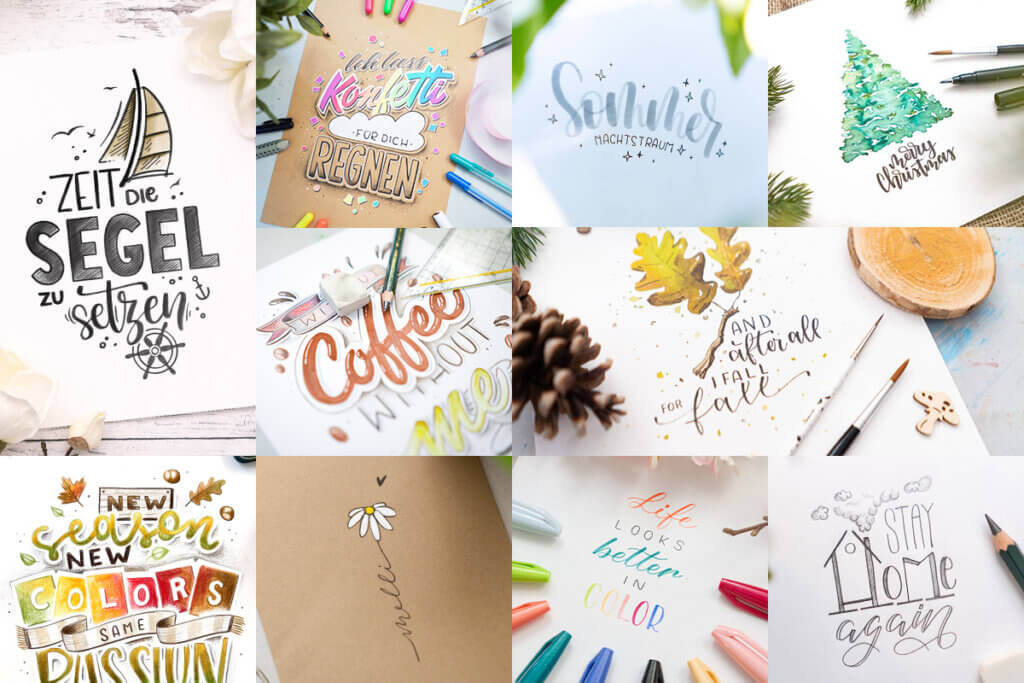
Du kannst noch so kreativ sein – manchmal brauchst du etwas Inspiration von außen! Daher möchte ich dir in diesem Artikel einfach mal ganz unterschiedliche Handlettering Ideen präsentieren, die zum Nachmachen anregen.
Ich verspreche dir: Wenn du alle Ideen angeschaut hast, wird es dir (wieder) in den Fingern kribbeln und du möchtest am liebsten sofort loslegen!
Ideen für Handlettering Techniken
Als erstes lohnt auf jeden Fall ein Blick auf die verschiedenen Handlettering Techniken. Je mehr Techniken du beherrschst, desto mehr Ideen kommen die automatisch für weitere Projekte.
Die wohl markanteste Komponente des Handletterings ist das Brushlettering. Dabei verwendest du zum Lettern einen Pinsel oder Brushpen. Wie das geht, erfährst du auf meinem Blog vor allem auf der Startseite.
Eine geniale Technik, um das Brushlettering zu imitieren, ist die Faux Calligraphy. Sie ermöglicht dir, die charakteristischen Strichstärkenkontraste des Brushletterings mit einem beliebigen Stift nachzuahmen.
Das Schöne an der Faux Calligraphy ist, dass sie auf praktisch jedem Untergrund funktioniert!
Möchtest du deinen Handletterings mehr Dynamik und Leben einhauchen, wirf einen Blick auf das sogenannte Bounce Lettering. Wie der Name schon sagt, bringst du deine Buchstaben mit dieser Technik zum Hüpfen bzw. Tanzen und kannst ganz neue Ideen umsetzen.
Etwas komplexer ist das Ribbon Lettering. Dank dieser genialen Lettering Technik ist es möglich, Schriftzüge im Stil eines Banners oder einer Banderole zu gestalten.
Du solltest das Ribbon Lettering unbedingt auf die Liste deiner Handlettering Ideen aufnehmen – die Ergebnisse sind immer wieder fantastisch!
Und wenn du schon voll konzentriert bist, habe ich gleich die nächste komplexe Technik für dich. Das Rope Lettering ist zwar etwas weniger anspruchsvoll, erfordert aber ebenfalls volle Konzentration.
Dabei imitierst du mit deinen Wörtern die Optik eines Seils und zauberst wunderbar maritime Schriftzüge.
Eine weitere schöne Handlettering Idee ist das 3D Lettering. Durch den Einsatz cleverer Effekte oder echter Perspektive bekommen deine Buchstaben damit einen dreidimensionalen Look und wirken noch beeindruckender.
In Layouts mit mehreren Wörtern kommen solche 3D Letterings besonders gut zur Geltung und erzeugen einen genialen Kontrast.
Andere Oberflächen als Papier
Nagut, bisher haben wir stets auf das Papier geschaut. Doch es gibt noch viele andere Untergründe und Oberflächen, auf denen du deine Ideen umsetzen kannst.
Ein Klassiker ist das Handlettering auf Porzellan, Glas oder Keramik. Damit eröffnen sich dir plötzlich ganz neue Möglichkeiten.
Du kannst nicht nur dein eigenes Geschirr verschönern, sondern einzigartige Geschenke für Freunde und Verwandte zaubern. Natürlich gehört auch hier wieder einiges an Übung dazu!
Ein weiteres, tolles Material aus der Natur ist Holz. Und auch das lässt sich beschriften. Unbehandelt ist es meist sehr rau und erfordert entsprechend robuste Stifte.
Ist das Holz lackiert, wird die Oberfläche deutlich glatter und du kannst präziser schreiben. Besonders die Gestaltung von Holzschildern macht immer wieder super viel Spaß und beschert dir tolle Unikate. Aber auch Kisten, Holzscheite oder ganze Holzmöbel lassen sich mit Handletterings verschönern.
Wo Glas und Holz genannt werden, dürften Steine nicht fehlen! Die Bemalung von Steinen ist eine uralte Tradition. Detaillierte Wörter und Schriftzüge machen die behandelten Steine aber nochmals schicker.
Durch die verschiedenen Formen ist dabei jeder Stein eine neue Herausforderung. Am schönsten ist das Steine beschriften natürlich dann, wenn die Steine auch noch selbst gesammelt sind.
Nach den eher harten Materialien bleibt noch ein flexibles Gegenstück übrig: Stoff! Stoff lässt sich nicht nur maschinell bedrucken, sondern auch wunderbar per Hand beschriften.
Ob Kleidung, Handtücher oder Schuhe – mit einem Handlettering wird alles schöner. Na, schon eine Idee welches Stück in deinem Kleiderschrank sich eigenen würde!?
Zu guter Letzt noch der Hinweis auf organische Untergründe. Wie wäre es denn mal mit einem Lettering auf einem Blatt oder sogar deiner Haut?
Ideen für neue Projekte
An dieser Stelle möchte ich dir noch ein paar Ideen präsentieren, die mit Sicherheit Lust auf neue Handlettering Projekte machen.
Im Herbst kannst du beispielsweise auch mal auf einer Kastanie schreiben. Dazu musst du sie gründlich reinigen und anschließend kannst du mit einer feinen Stiftspitze loslegen. Mal wieder ein ganz anderes Gefühl!
Auch Kerzen lassen sich wunderbar beschriften. Damit werden deine Letterings wieder völlig neu in Szene gesetzt.
Um deine Wörter auf eine Kerze zu bringen, kannst du entweder direkt darauf schreiben oder dein Handlettering mit einer genialen Technik auf die Kerze transferieren.
Wer sagt eigentlich, dass Schrift immer geschrieben werden muss? Sie lässt sich auch wunderbar ausschneiden!
Dabei entstehen manchmal auch ganz zufällig tolle Vorlagen, die man am liebsten sofort umsetzen möchte!